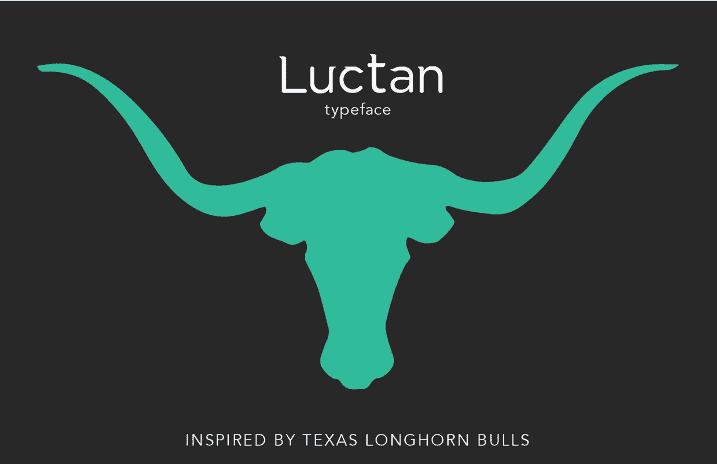
Luctan Typeface
A Luctan Typeface é uma elegante tipografia de sans-serif desenvolvida pelo designer Hamilton. Este tipo de letra combina simplicidade com uma pitada de sofisticação, sendo perfeita para projetos que exigem um estilo limpo e moderno. Seus contornos retangulares e leves trazem um ar distinto sem perder a facilidade de legibilidade essencial das tipografias em formaless serifadas. Ideal para criações digitais como websites, editoriais online ou até mesmo cartões de visita profissionais, a Luctan atinge o equilíbrio entre modernidade e elegância. Seja você designer gráfico ou criador de conteúdo digital, esta fonte pode tornar sua produção ainda mais impecável e sofisticada.